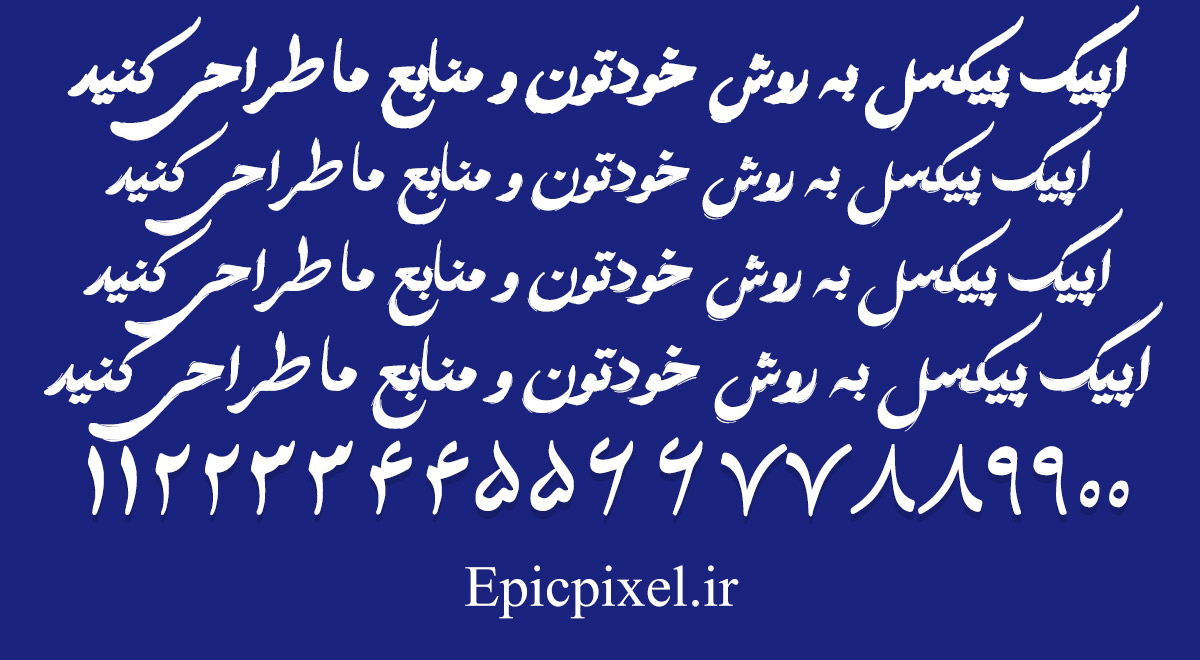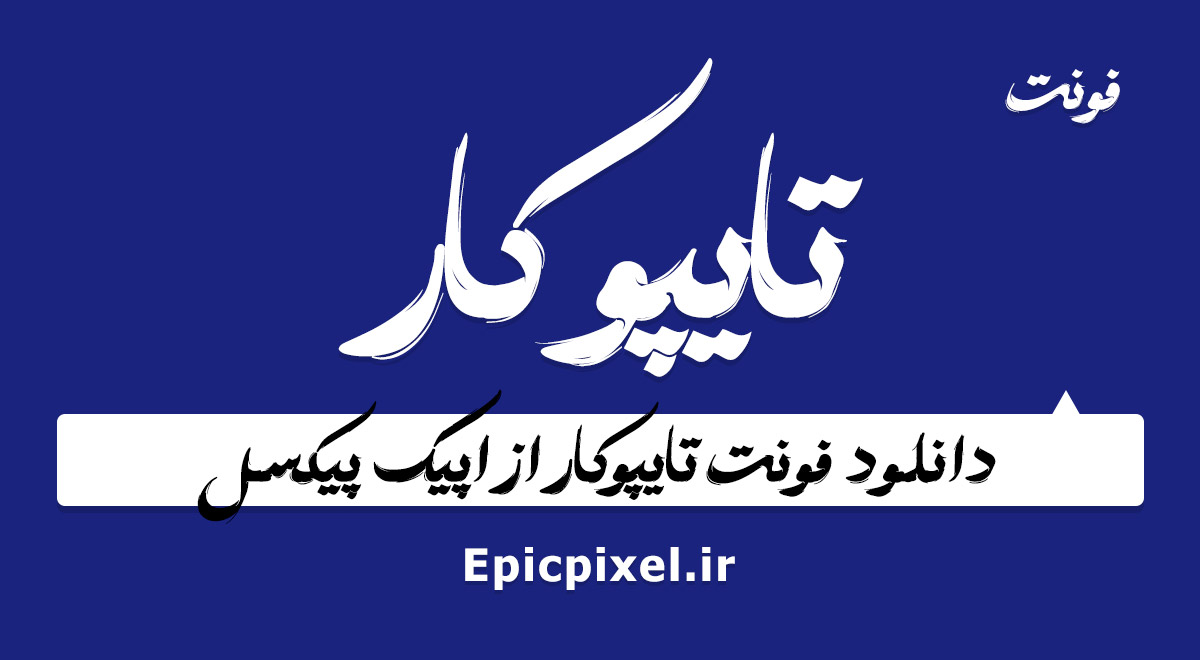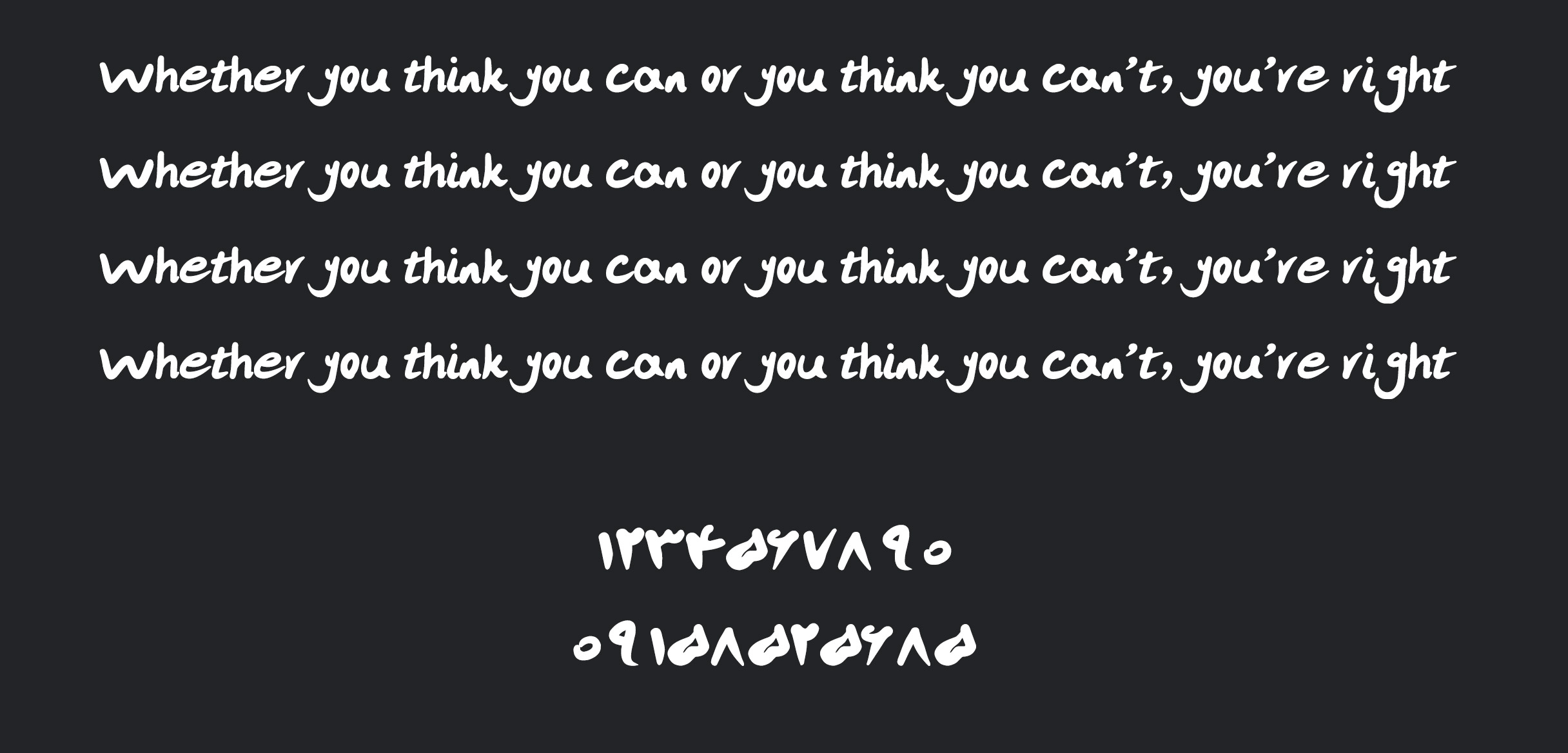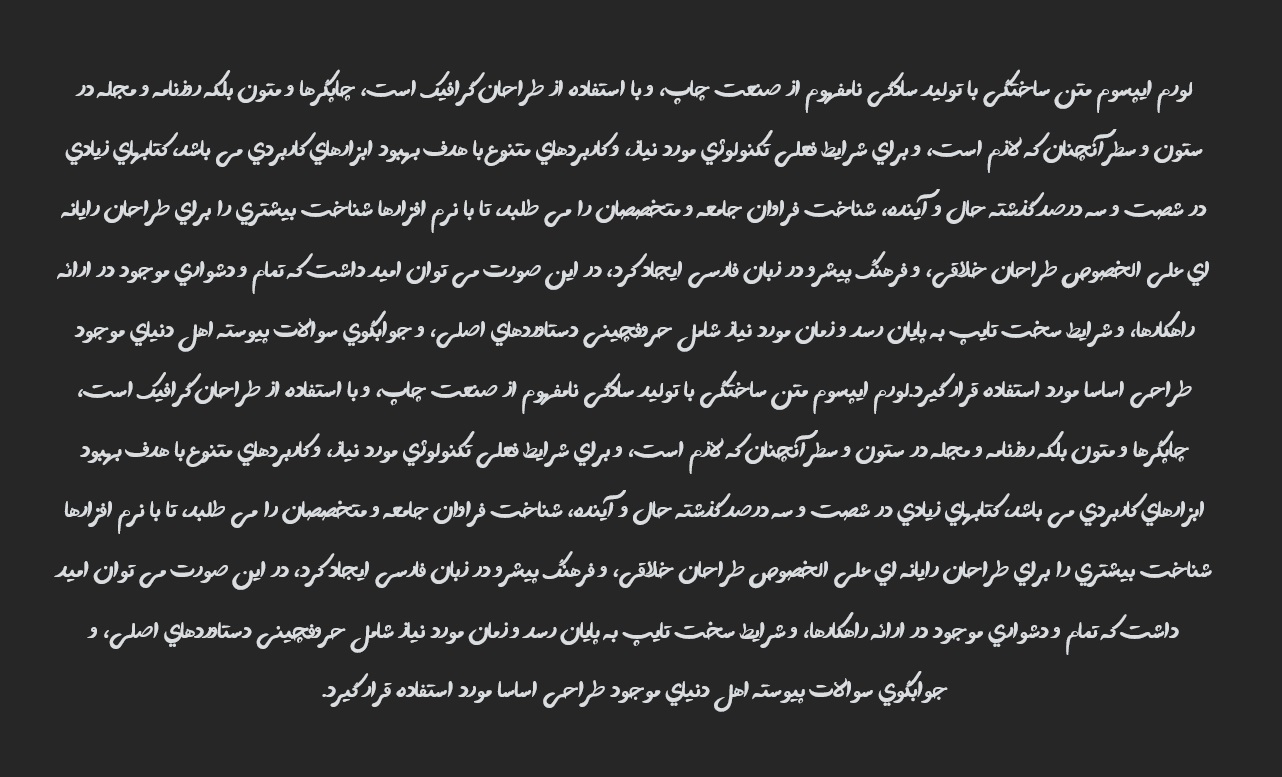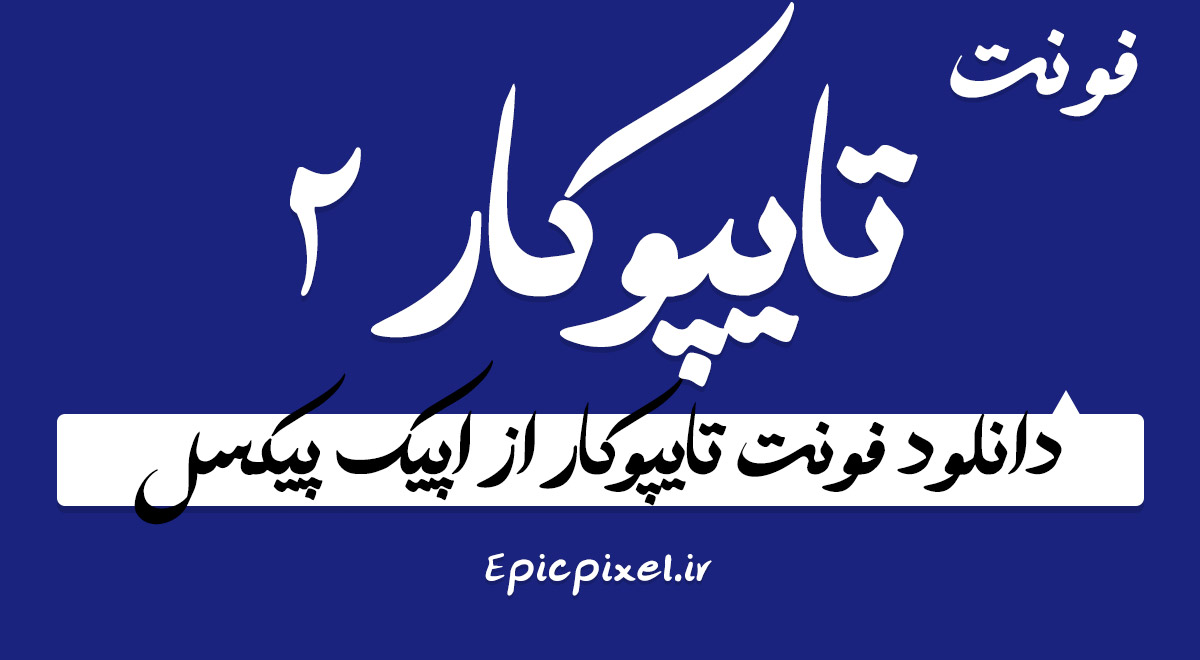
| ⭐ توضیحات | مجموعه ای کامل از فونت های تایپوکار و نسخه شبیه سازی شده بنام اپیک تایپوکار فونت اپیک تایپوکار با پشتیبانی از حروف فارسی / انگلیسی ( لاتین )، اعداد فارسی Fu Num و انگلیسی بهمراه نسخه وب |
فونت تایپوکار یک انتخاب برای طراحان خلاق
فونت تایپوکار یک مجموعه از فونتهای دستنوشته است که برای تایپوگرافی و طراحی مناسب است. این فونتها دارای ویژگیها و مزایایی هستند که آنها را از سایر فونتها متمایز میکند. در این مقاله به بررسی دو فونت از این مجموعه و نحوه دانلود و استفاده از آنها خواهیم پرداخت.
دانلودفونت تایپوکار معرفی و ویژگی ها
فونت تایپوکار، نام یک کالکشن از فونت های فارسی است که با نام مستعار تایپوکار ساخته شده است. این کالکشن شامل چندین فونت به صورت دست نویس، رسمی، خوشنویسی و فانتزی است که در این سایت منتشر شده.
فونت های تایپوکار دارای ویژگی های منحصر به فرد و جذابی هستند. این فونت ها به صورت کاملا شخصی و با تلاش زیادی اجرا شده اند. این فونت ها شامل حروف فارسی و انگلیسی می باشند. این فونت ها دارای کشیدگی ها و حروف جایگزین و امکاناتی هستند که در زیبایی یک طرح کمک بسزایی می کنند. از منوی glyphs می توانید به این موارد دسترسی پیدا کنید. این فونت ها بر روی موبایل در برنامه هایی نظیر inshot, picsart و … تست و اجرا شده اند.
فونت های تایپوکار
فونت اول: دستنویس فانتزی
فونت اول از کالکشن فونت تایپوکار، یک فونت جدید دست نویس فانتزی است. این فونت با الهام از سبک های مختلف نقاشی و خط طراحی شده است. این فونت دارای حروف بزرگ و کوچک، علائم نگارشی، علائم ریاضی، علائم والاتور، علائم پول، علائم سرو صدا، علائم علم الحروف، علائم سطح بالا، علائم سطح پایین، علائم جبر، علائم زبان شیرین، علائم
فونت دوم: دستنویس خوشنویسی
فونت دوم از کالکشن فونت تایپوکار، یک فونت زیبا و شیک دست نویس خوشنویسی است. این فونت با الهام از سبک های مختلف خط فارسی و اسلامی طراحی شده است. این فونت دارای حروف بزرگ و کوچک، علائم نگارشی، علائم ریاضی، علائم والاتور، علائم پول، علائم سرو صدا، علائم علم الحروف، علائم سطح بالا، علائم سطح پایین، علائم جبر، علائم زبان شیرین، علائم زبان عربی، علائم زبان انگلیسی، علائم زبان فارسی، علائم زبان ترکی، علائم زبان اردو، علائم زبان کردی و علائم زبان های دیگر می باشد. این فونت برای نوشتن متن های رسمی، مذهبی، ادبی، تاریخی، فرهنگی و هنری مناسب است.
دانلودفونت سوم: رسمی و مدرن
فونت سوم از کالکشن فونت تایپوکار، یک فونت با کیفیت و زیبا رسمی و مدرن است. این فونت با الهام از سبک های مختلف تایپوگرافی و طراحی گرافیک طراحی شده است. این فونت دارای حروف بزرگ و کوچک، علائم نگارشی، علائم ریاضی، علائم والاتور، علائم پول، علائم سرو صدا، علائم علم الحروف، علائم سطح بالا، علائم سطح پایین، علائم جبر، علائم زبان شیرین، علائم زبان عربی، علائم زبان انگلیسی، علائم زبان فارسی، علائم زبان ترکی، علائم زبان اردو، علائم زبان کردی و علائم زبان های دیگر می باشد. این فونت برای نوشتن متن های کسب و کار، آکادمیک، علمی، تحقیقاتی و خبری مناسب است.